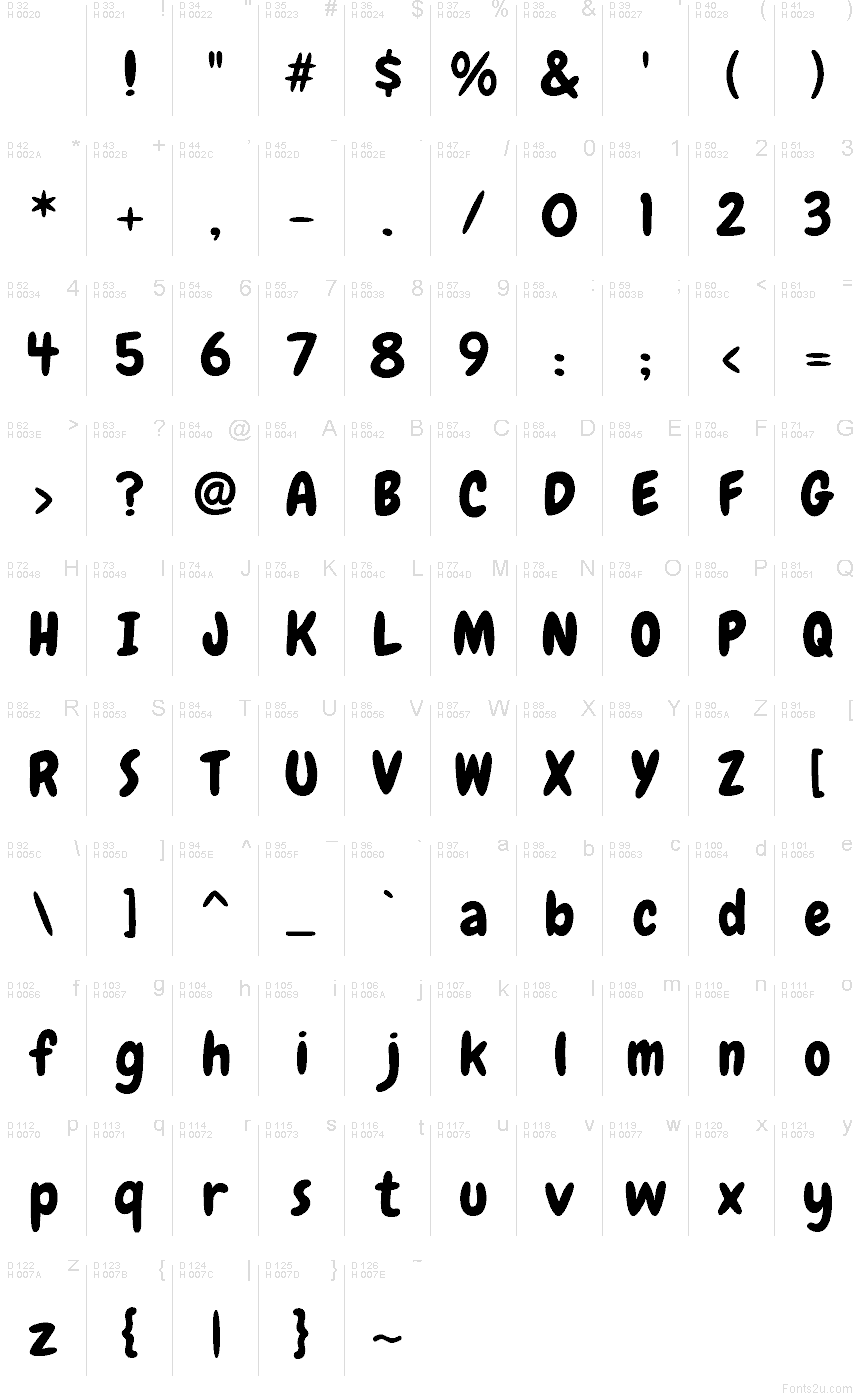
Chewy Cyr Regular
Chewy Cyr, da Font Diner, é uma fonte brush gratuita definida por um ritmo flutuante e envolvente que dá às letras um aspecto de terem sido moldadas, em vez de formalmente desenhadas. Seus traços arredondados e curvas suaves criam uma cadência agradável, proporcionando ao design um calor que remete à pintura manual, sem parecer rústica ou grosseira.
Esse ritmo dinâmico torna a fonte perfeita para títulos curtos em embalagens de snacks, menus de café, etiquetas de padaria, títulos de desenhos animados e posts nas redes sociais. Sempre que a simpatia for mais importante do que a geometria estrita, a Chewy Cyr traz um toque relaxado e autêntico para adesivos e flyers de eventos.